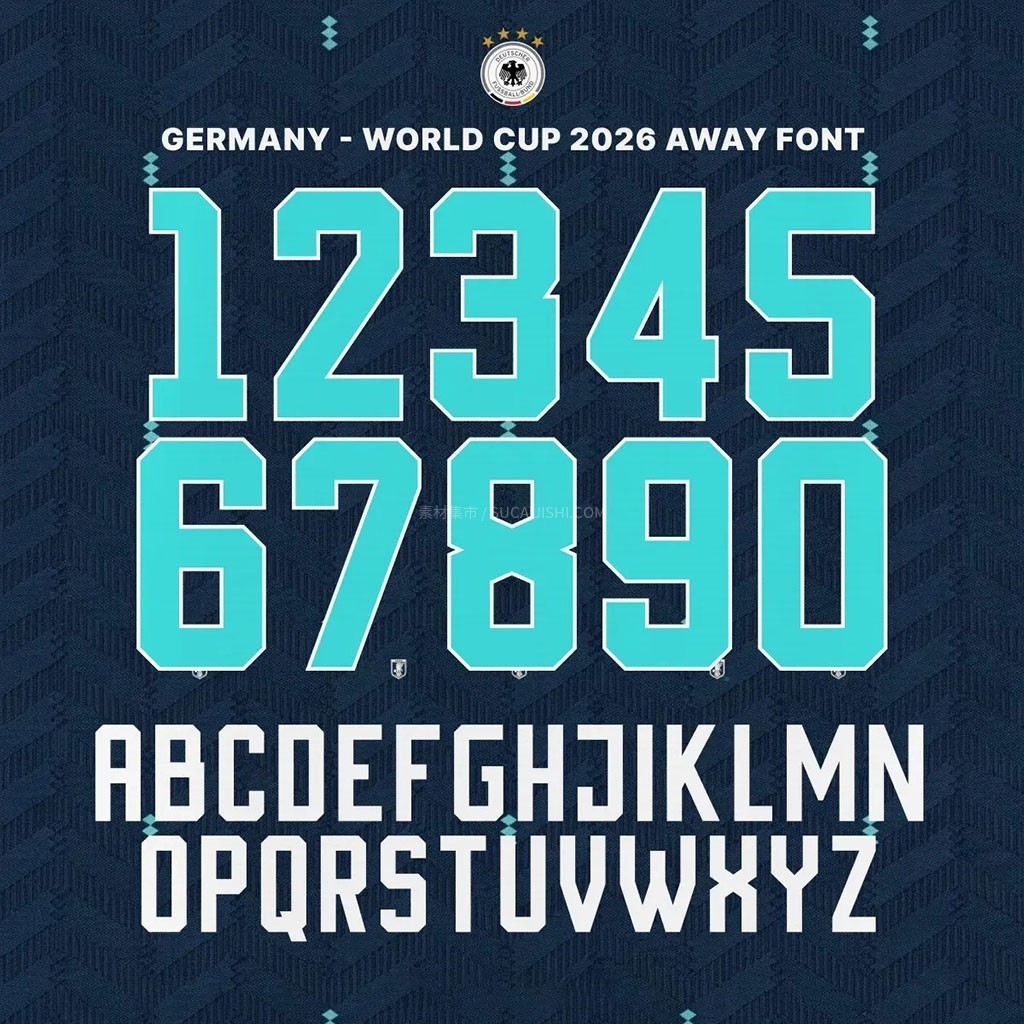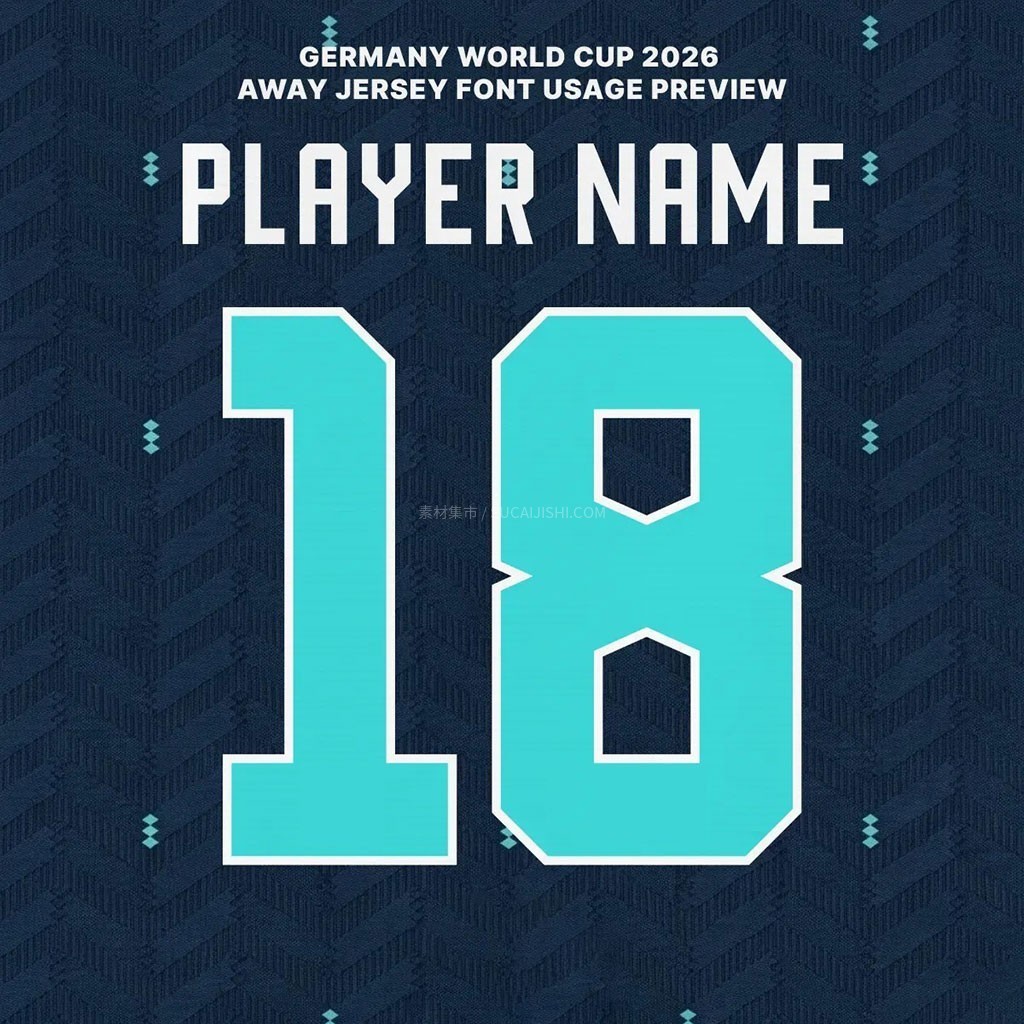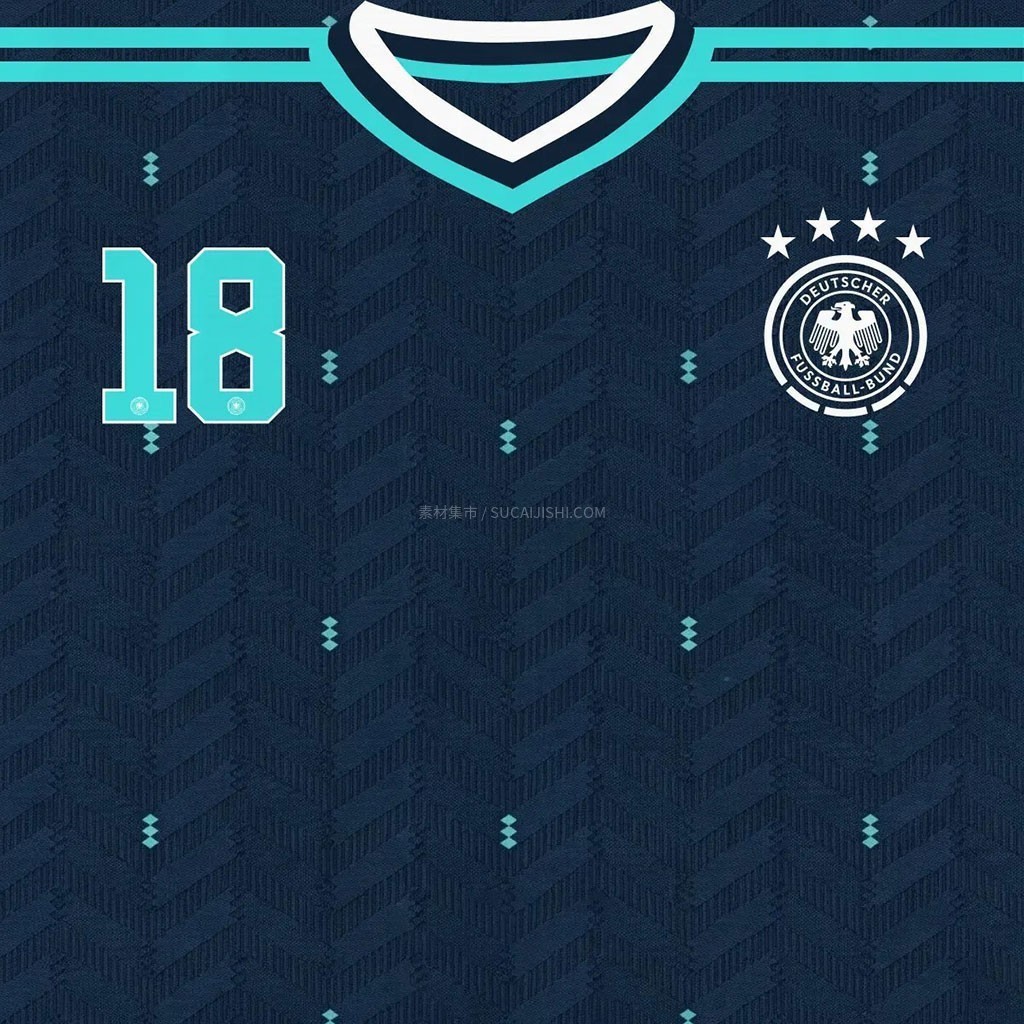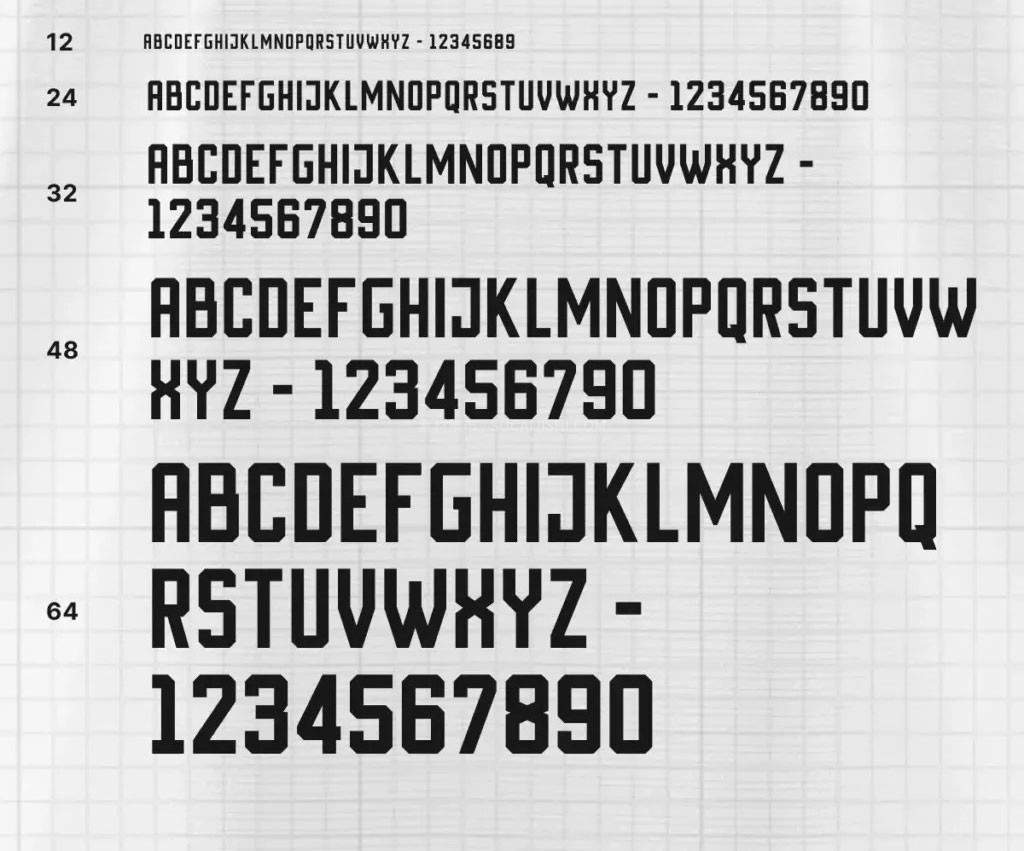
2026世界杯德国队客场球衣字体
这款字体的设计灵感深度汲取自德国国家队 2026 年世界杯客场战袍。它将德式足球精准、严谨且充满现代感的视觉风格完美融入数字艺术之中。字体经过高精度建模与调校,完美复刻了深色球衣上那套极具辨识度的视觉系统:流畅的字母线条,搭配醒目的薄荷绿/蓝绿色调,以及清晰利落的白色轮廓线,在保持动感的同时尽显现代优雅气质。